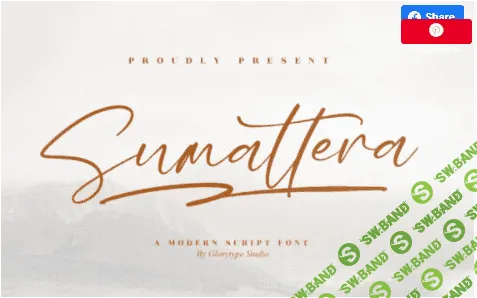
Название: Sumattera Font (2022)
[creativefabrica] Sumattera Font (2022)
Sumattera — это тонкий и изящный рукописный шрифт. Это лучший выбор для создания привлекательных логотипов, брендинга и цитат. Этот шрифт имеет кодировку PUA, что означает, что вы можете легко получить доступ ко всем удивительным глифам и лигатурам!